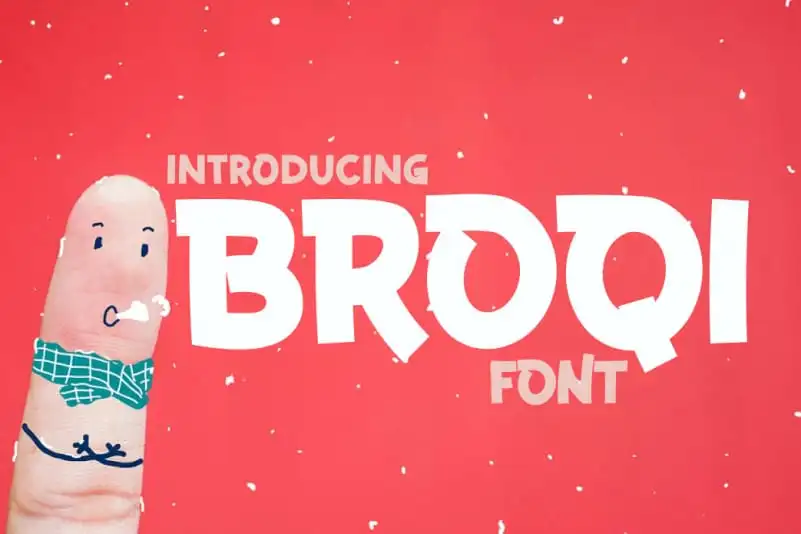
A Broqi Display Font é uma elegante escolha para projetos digitais que exigem estilo moderno e flexibilidade. Com aparência sólida e vibrante, esta fonte tem um charme atraente para diferentes formatos de design. Seu aspecto robusto, claro e determinado complementa os elementos visuais com precisão e beleza, tornando-a uma opção preferencial em qualquer projeto que você estiver desenvolvendo. A Broqi Display é perfeita para criar um design moderno e minimalista, destacando sua personalidade única em um ambiente de trabalho digital. Esta fonte não apenas dá vida aos seus designs digitais, mas também ajuda a comunicar seu ponto de vista com estilo e eficácia.